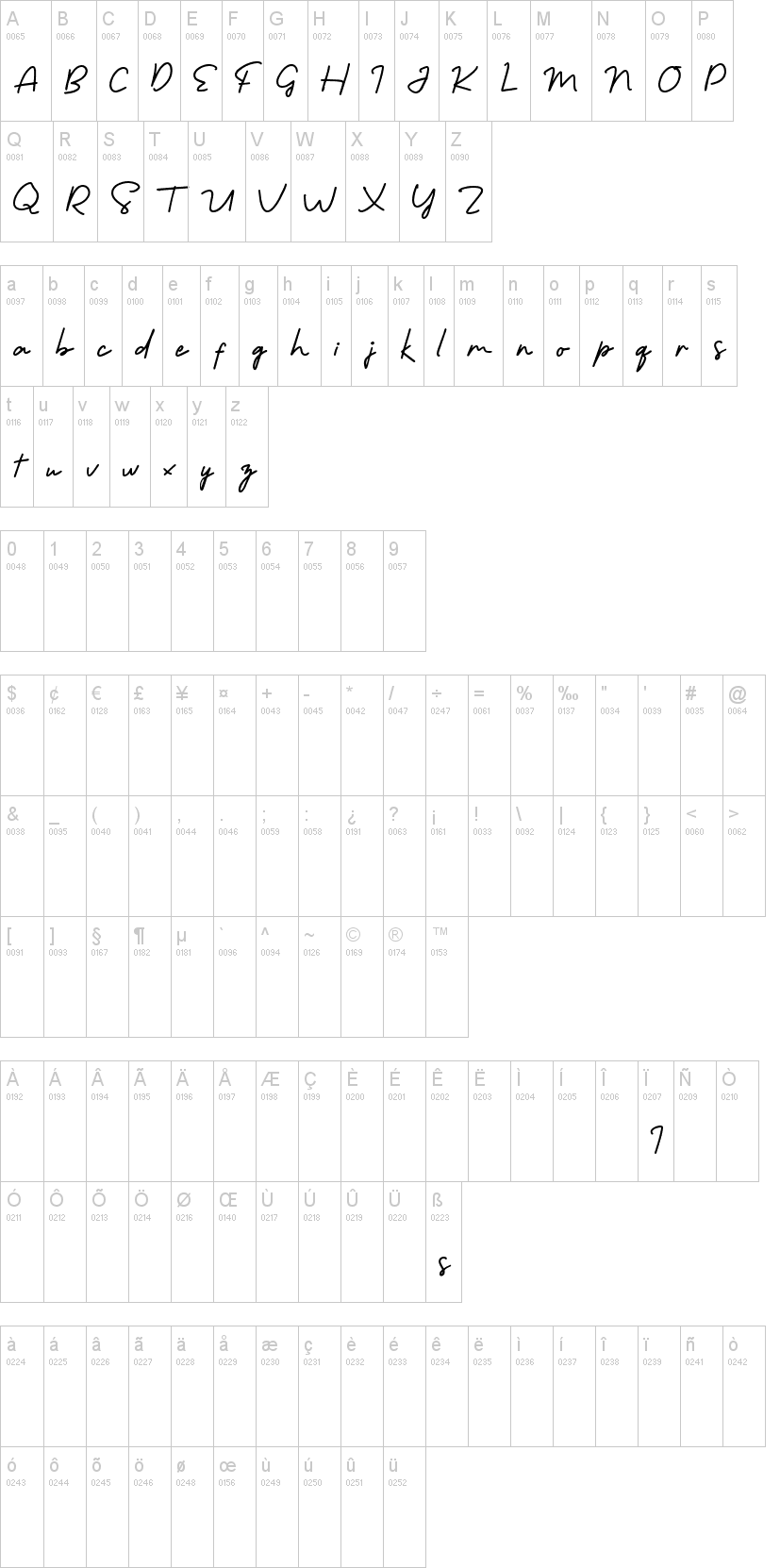
Morning Gold
Morning Gold 是一种非常漂亮的手写风格字体,由字体设计师 Dikas Studio 设计。这个字体非常适合用于时尚、美容、咖啡厅、摄影、婚礼等场景的设计。 该字体具有非常漂亮的流畅曲线和优雅的笔画,字母之间的间距非常合适,使得整个字体看起来非常和谐。Morning Gold 还配备了许多特殊字符、替代字母和花哨的连字,这使得它的设计非常灵活,可以让设计师在创作中更有创意。 总之,如果你正在寻找一种漂亮而又多样化的手写风格字体,Morning Gold 绝对是一个不错的选择。
Morning Gold是一款非常不错的手写艺术字体,具有很好的视觉感,适合于文化类的宣传设计、商业类品牌的广告和产品包装设计以及个性化文字排版等较多场景。
Morning Gold字符映射图